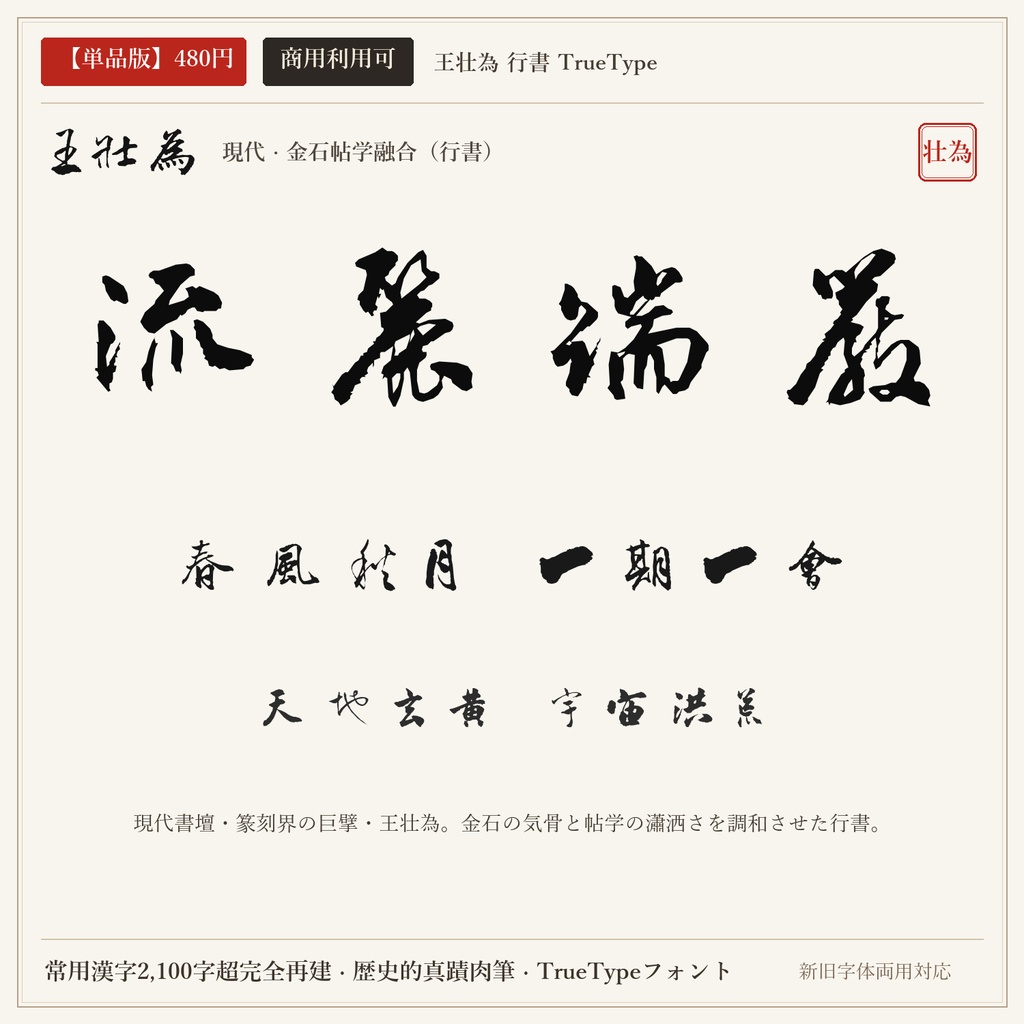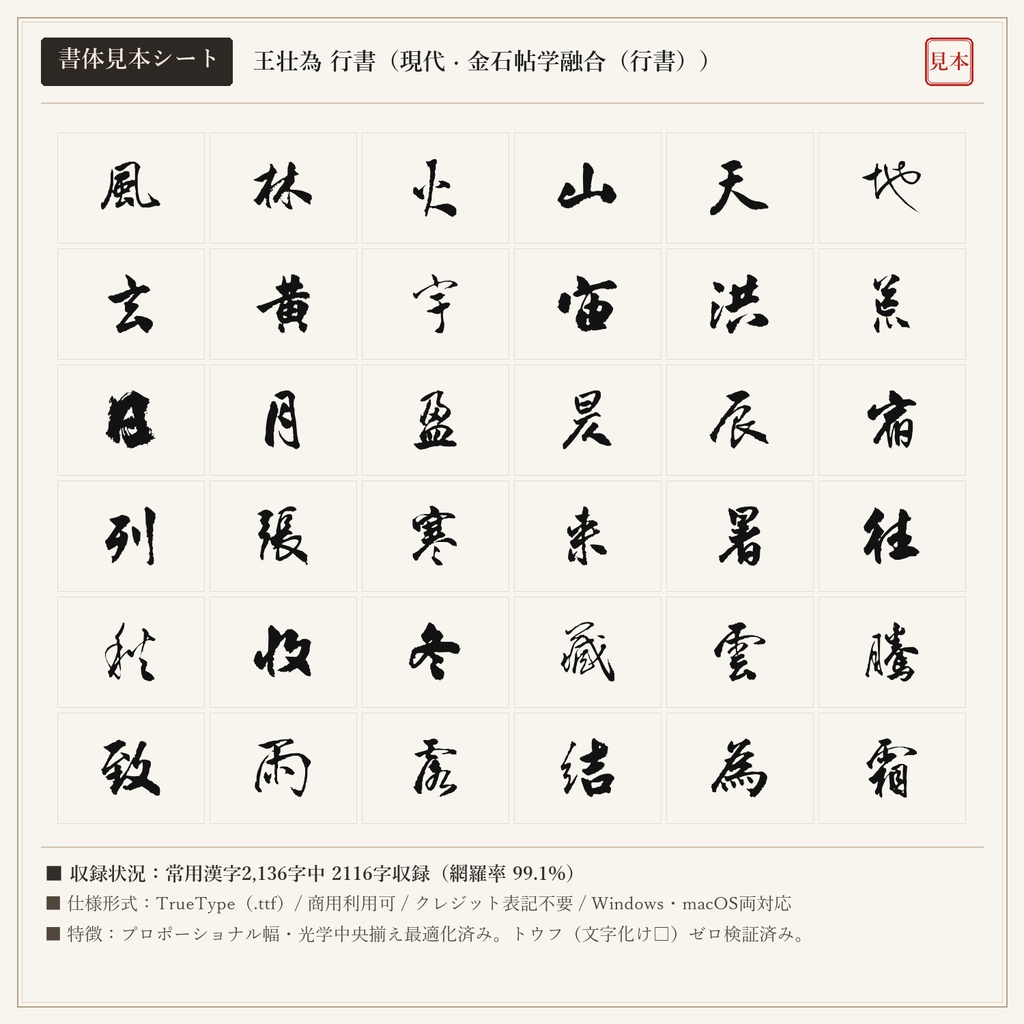
【単品版】王壮為 行書フォント|近代現代行書の巨匠・金石気帯びる流麗・商用利用可
台湾書壇の指導者として現代書道界に絶大な足跡を残した王壮為の肉筆行書から制作されたフォントです。古代金石文の骨格と二王の優雅な筆法が高次元で調和し、現代のデザインにも美しく調和します。 ■ 本フォントの特徴 ・常用漢字2,136字中、2116字を高精度収録(網羅率 99.1%)。 ・現代の新字体を入力しても、歴史的な真蹟字形・旧字体が自然に出力されるデュアルマッピング対応。 ・文字ごとの最適なプロポーショナル字幅設定により、自然で流麗な連綿と墨の息遣いを再現。 ・トウフ(文字化け□)を出さない事前フォントマッピング検証済み。 ■ 未収録文字一覧(全20字) 歴史的真蹟・拓本に存在しない以下の字種は未収録(非対応)となります。ご購入前にご確認ください。 丼 刹 咲 唄 堀 峠 拶 枠 栃 桁 濫 疎 線 脊 菓 著 込 郷 闘 駄 ■ 形式 TrueTypeフォント(TTF) / Windows・macOS両対応 ■ 利用規約 個人・法人の商用利用OK。クレジット表記不要。 ロゴ、動画、ゲーム、書籍、同人誌、配信サムネイル、Web、印刷物、グッズ等に自由にご使用いただけます。 フォントファイル自体の再配布・共有・販売・転売は禁止です。 ※東晋の王羲之(行書)と盛唐の顔真卿(楷書)を同梱した「【無料版】王羲之 + 顔真卿 2書体セット(0円)」もショップ内にて無料配布中です。